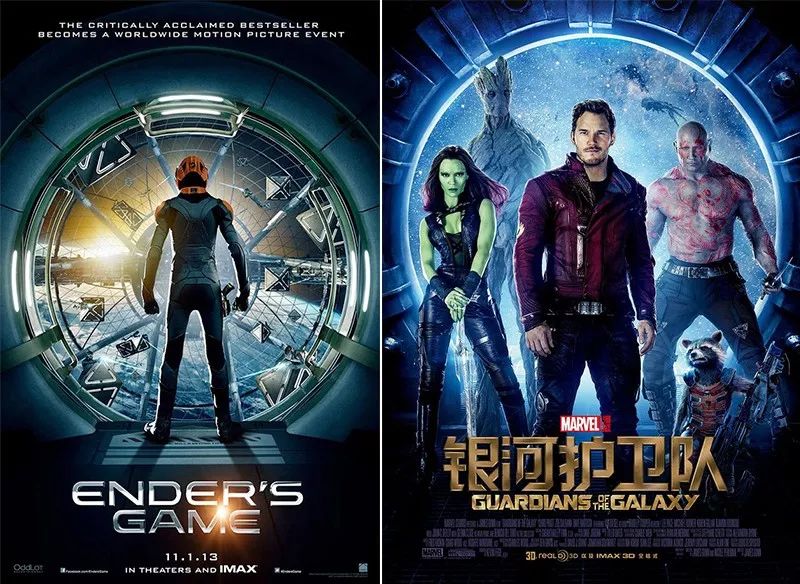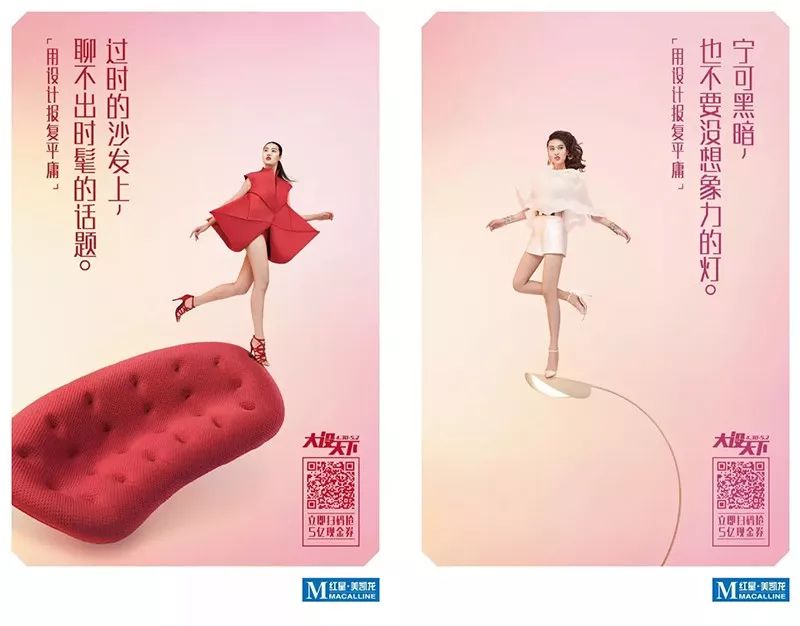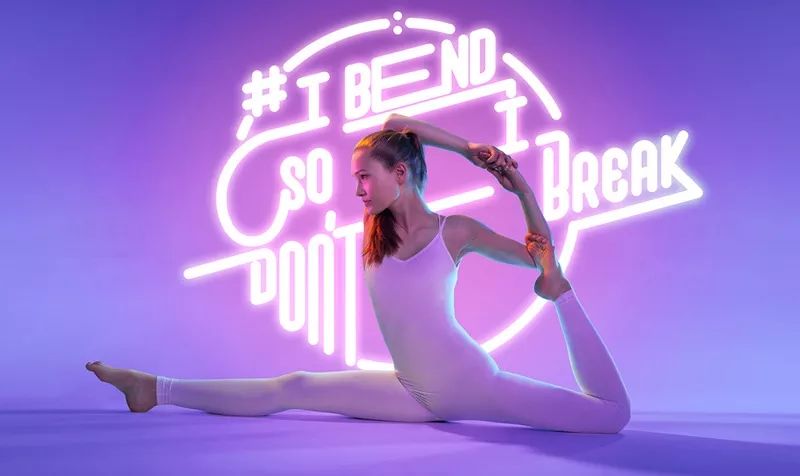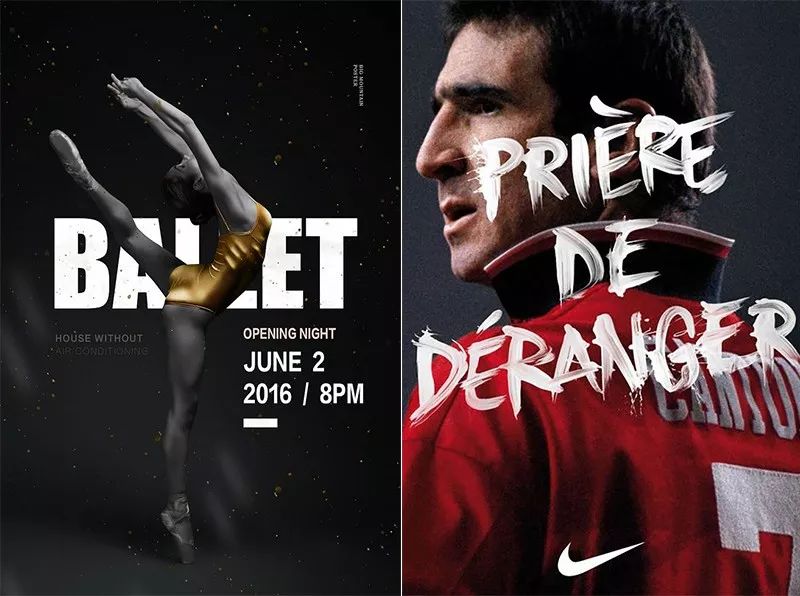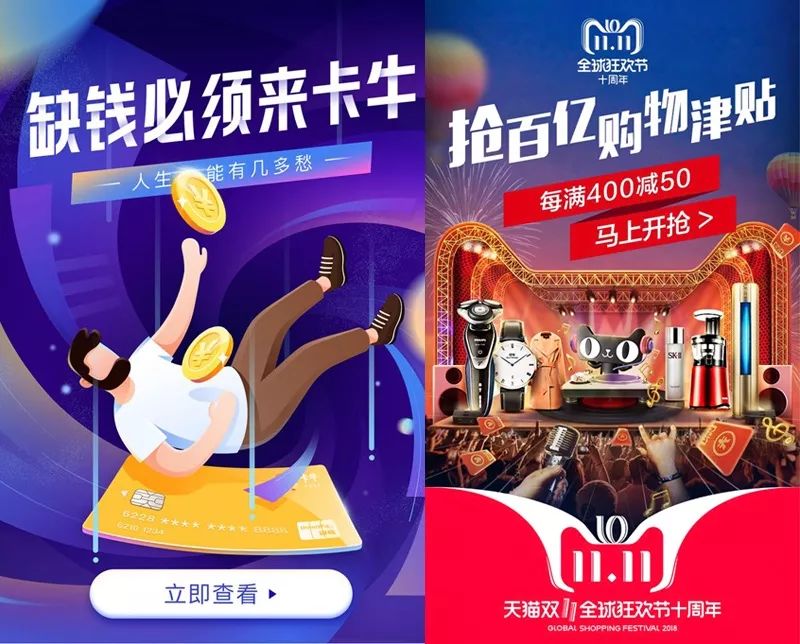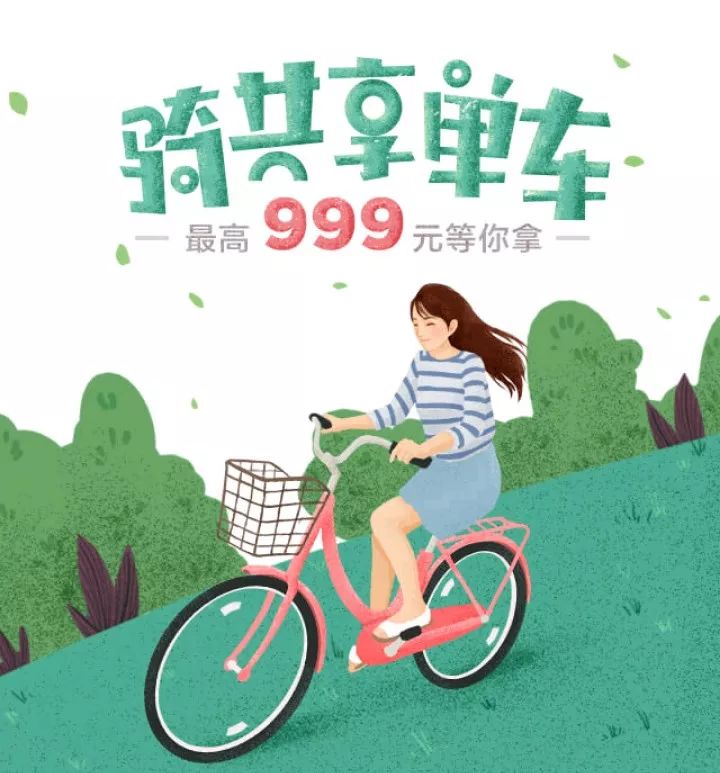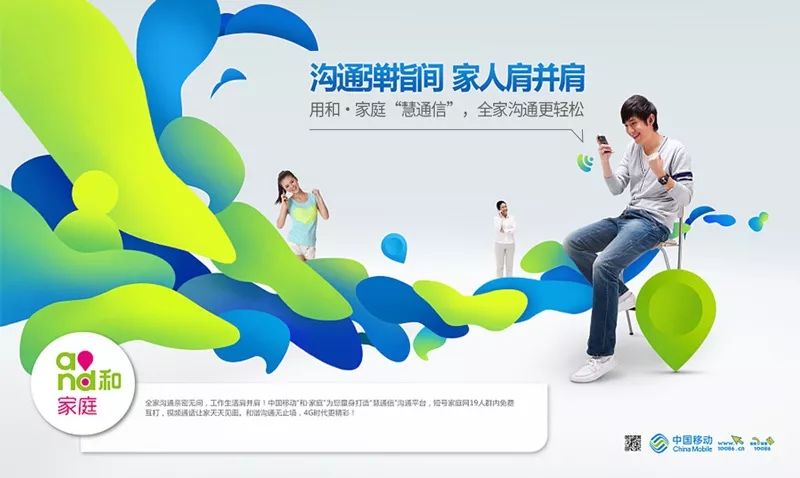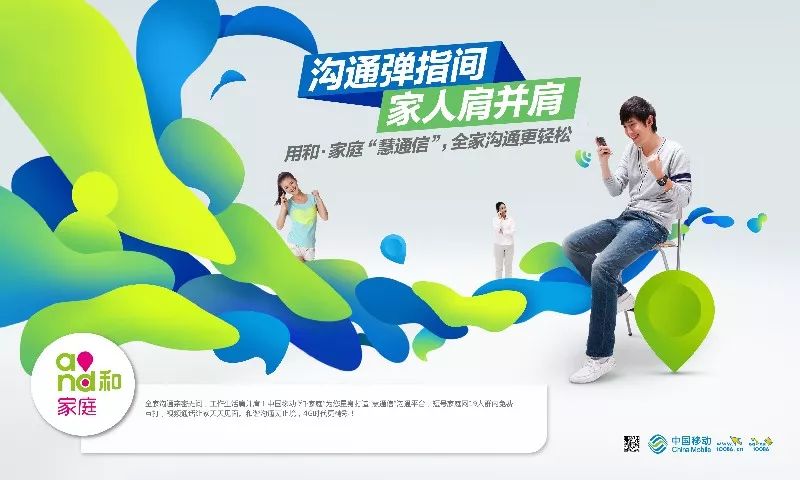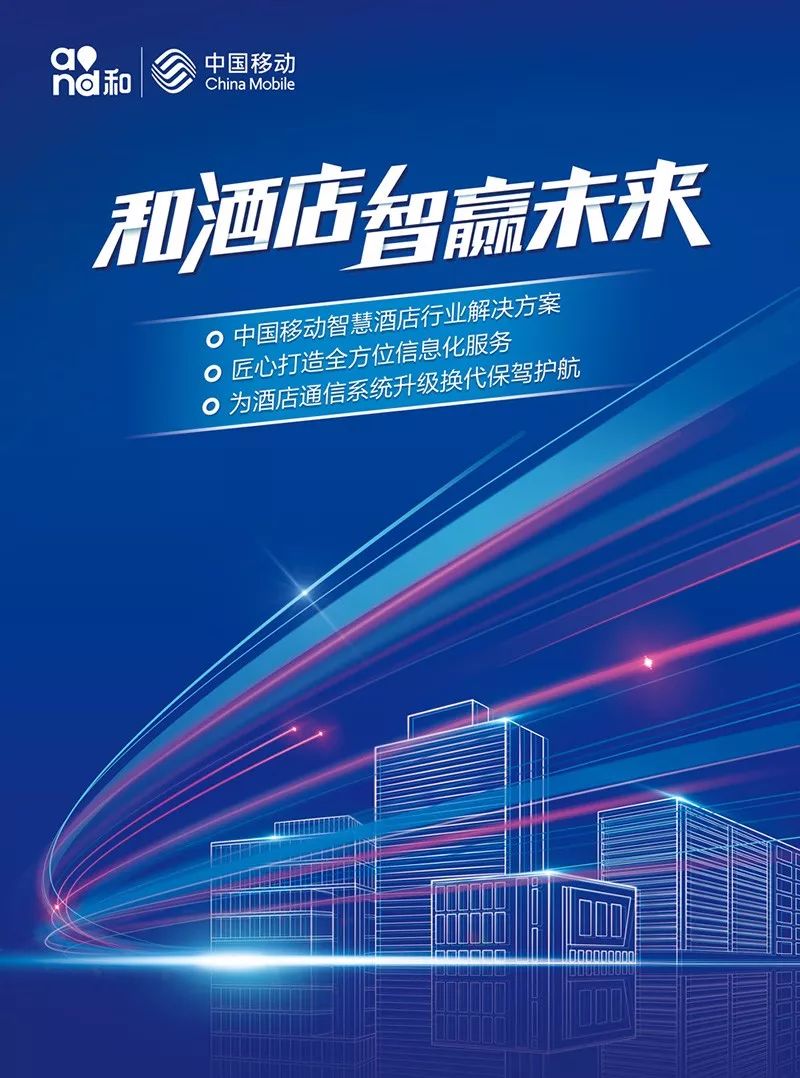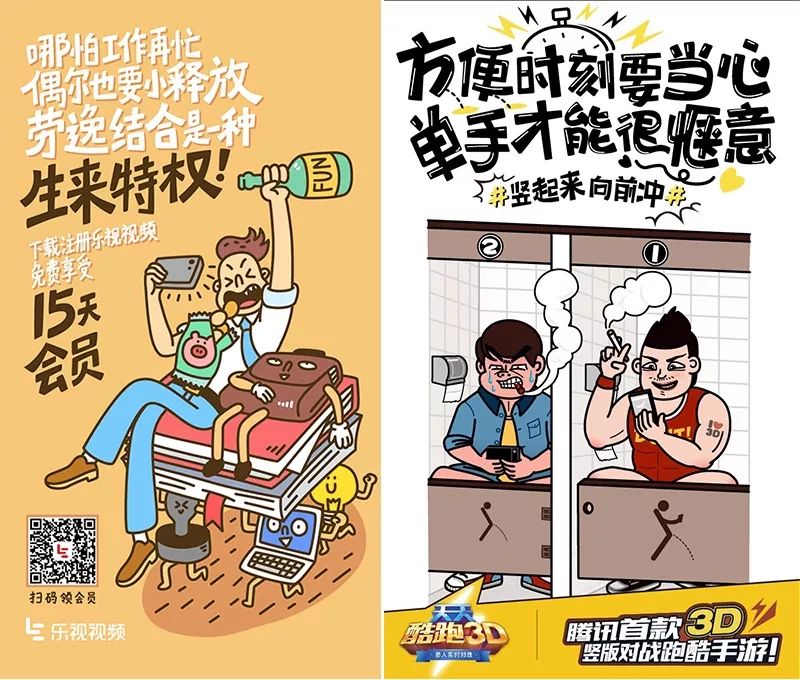
如何打破粗暴的标题设计?四个方面改进标题设计
为了使一张海报或者广告画面变得更精彩,我们通常会把图案部分作为视觉主体,这个主体往往是创意、形式、视觉冲击力的集中体现,设计师会花比较多的时间来处理,但对于如何处理画面中的文字,很多人则会偷懒。以至于有很多海报的图案部分很精彩,但是标题、副标题、主要卖点等信息的设计很粗暴,这些粗暴的标题是哪里出了问题呢?发现主要有以下四个方面的原因:
//  一、字体与画面风格不符  //
每一种字体都有它的性格,所以我们要根据画面的风格和调性来选择一种与它匹配的字体,有些设计师会把自己喜好的、或者最近比较流行的字体用在每张画面上,这显然是不行的。比如画面调性偏向女性的海报使用腾翔潮黑体就不太合适,因为该字体的笔画太粗太硬,与女性的温柔、优雅很不搭。
偏向女性的字体,字形一般会比较修长,笔画相对柔软、纤细、多弧线,比如方正正纤黑、汉仪晓波美妍体、方正姚体、汉仪清雅、汉仪润圆、造字工房形黑都是具有这些特点的字体,如果实在找不到合适的字体,或者没有字体版权,我们就要自己设计字体,具体的设计方向可以去网上找找参考。
上图的标题换了一种字体后,画面的粗暴感立即就消失了有没有?
另外,年轻时尚的画面适合搭配笔画简单、硬朗,但又不是太厚重的字体。
温馨的画面适合搭配比较含蓄的手写体。
运动海报的标题适合使用笔画较粗、较硬朗的无衬线体、或者很有气势的书法字体。
//  二、没细节  //
粗暴的反义词是精致,而精致的设计往往是很注重细节的,所以没有细节也是导致标题粗暴的常见原因。例如很多人排标题不管画面是怎样的,通通都是把文字拉大,然后左对齐或居中对齐放在画面空白处,副标和卖点全部紧跟着主标。这样的标题即使选对了字体也可能会显得很粗暴,例如下图的banner。
下图处理的就要好很多。
那么,如何增加标题的细节呢?有三种方法:
1.在字形上做一些变化
字库里的字体相对来说会比较常规,而在设计标题的时候,我们可以在保证其识别性的前提下大胆尝试,比如做一些笔画的连接、在笔画中融入图形、或者把某些笔画做一点适当的变形等等,都可以让标题看起来更精致。
2.增加辅助元素
利用一些装饰元素来辅助标题的排版与设计,也可以使其变得更精致,比如加入色块、线条、符号、图形等等。
▲上图通过给文字增加色块来丰富标题的细节
▲上图给标题文字加了胶片图形和直线
3.丰富文字的质感和效果
除了在文字轮廓上做文章外,我们还可以通过给文字增加材质来丰富标题的细节,最常见的材质和效果有立体字、金属字、描边字、发光字、在文字中嵌入图形等等。
▲金属字效果
▲立体字结合建筑元素
▲给文字填充图形(底纹)
//  三、设计风格与画面不符  //
有些标题设计可能在字体的选择方面并没有什么问题,也有一定的细节,但是仍会给人很粗暴的感觉,为什么呢?很可能是因为标题的设计形式或风格与画面不匹配,比如给温馨可爱的画面,搭配一个很硬朗很厚重的立体字标题,或者用方形色块来设计标题,都不太合适。
前面我们说了给标题增加元素和效果可以使其更有细节,但是做加法并不总是有效,有时候甚至会起反作用,比如在上图的画面中已经有很多色块了,这时标题再用色块反而很难凸显出来,而且几何色块、错位、倾斜排版等这些元素和设计手法太硬,所以,这个标题给人的感觉也很粗暴。
▲对于上图这种情况,把标题排简单一点反而显得更精致。
在排标题时既不要偷懒,也不要生搬硬套一些排版技巧,而是要学会总结什么样的画面适合什么风格的标题设计。比如运用几何色块的排版常用于比较酷、比较时尚的画面中。
插画风格的画面,标题的排版通常不会太齐整。
促销海报的标题一般会比较大,而且适合做倾斜处理。
//  四、没层次  //
如果标题设计得有层次关系,变化就会丰富一些,所以也会显得比较精致,而想要创造层次关系其实就是要有对比,在标题设计中可以用到大量的对比,如字体对比、大小对比、粗细对比、厚度对比、颜色对比、材质对比等等。
所以我们很少看到某个画面的大标题会独立存在,更常见的是它会与副标题、引标、广告语或者核心卖点排在一起,这么排的好处除了能让信息更集中、视觉更聚焦以外,还能丰富标题的层次,使文字的排版更精致。
上图的标题在字体和设计风格方面都是对的,但是看起来也还是不怎么舒服,主要原因之一就是缺乏对比没层次。
把画面下方的小文字上移到标题下方,使标题与其形成鲜明的对比,层次出来后,效果就好多了。
标题不论是对于一篇文章还是一张广告画面,都起着至关重要的作用,所以一定要重视,而且需要注意,在设计标题时不能把它当成一个独立的个体来设计,而是要呼应整个画面的风格和调性。总之,选对字体和设计风格、增加一点细节和层次,我们就可以打破粗暴的标题设计。